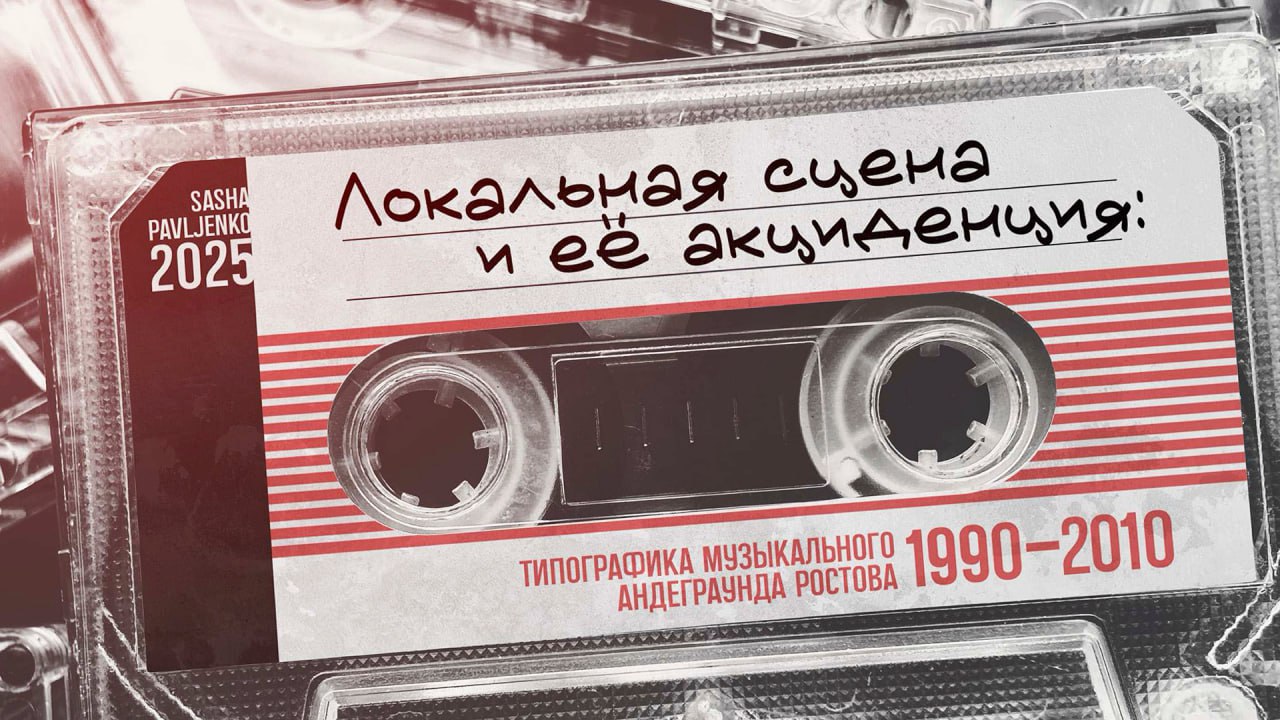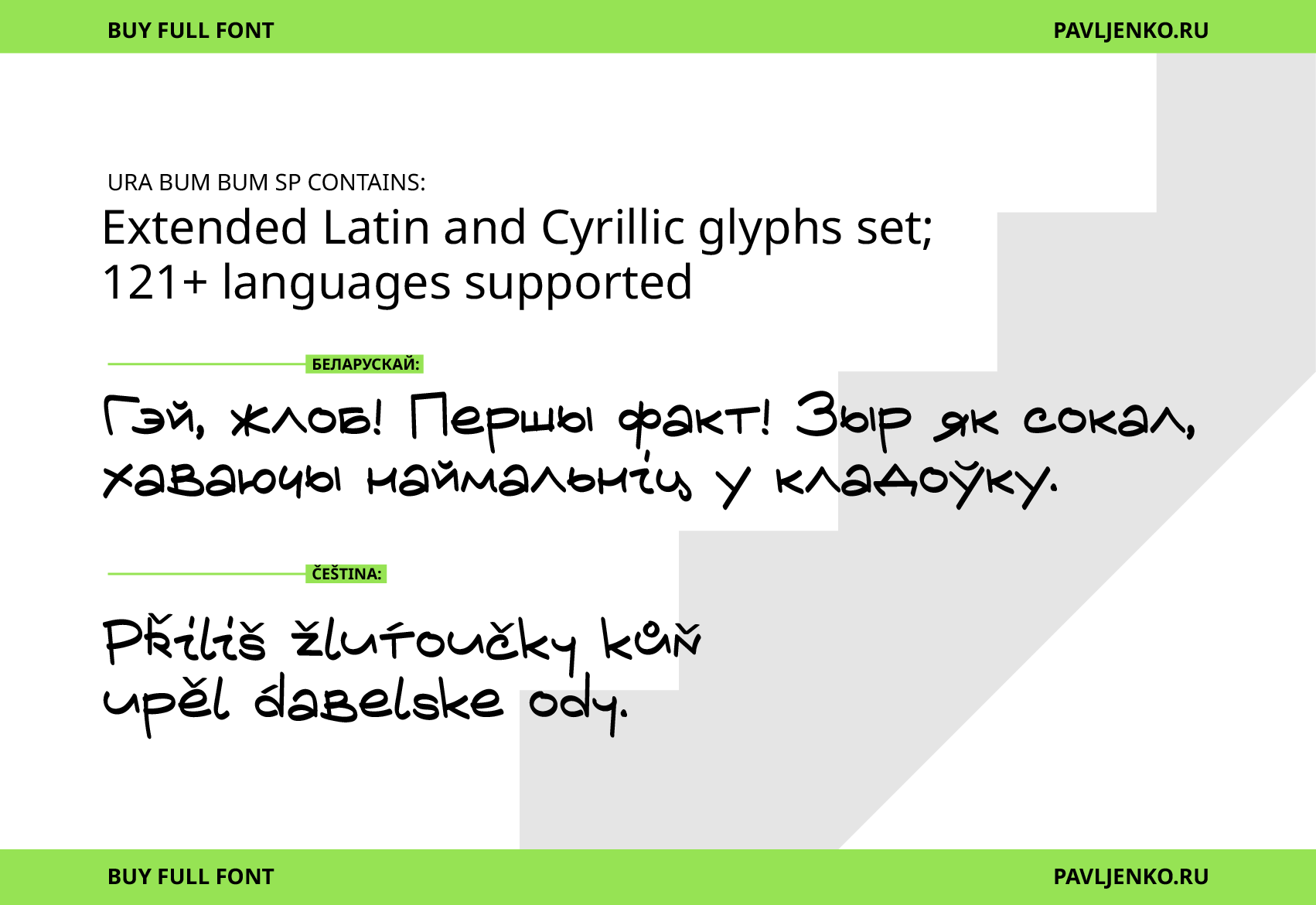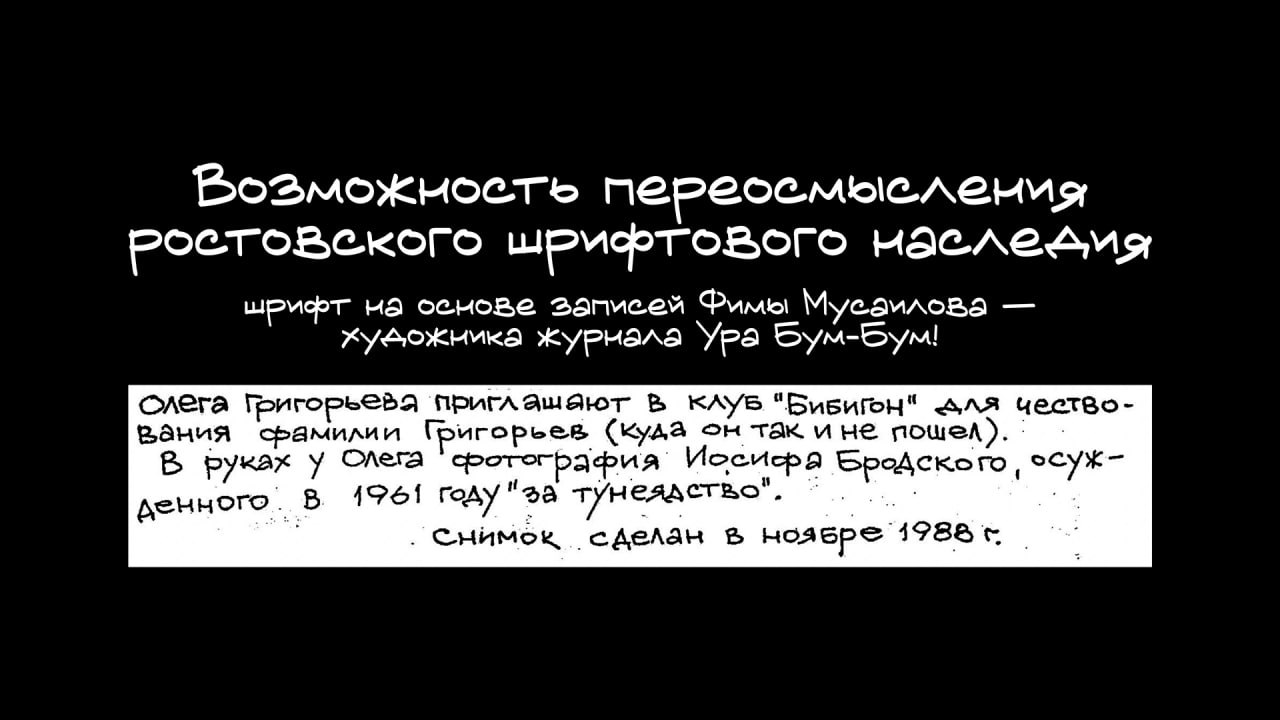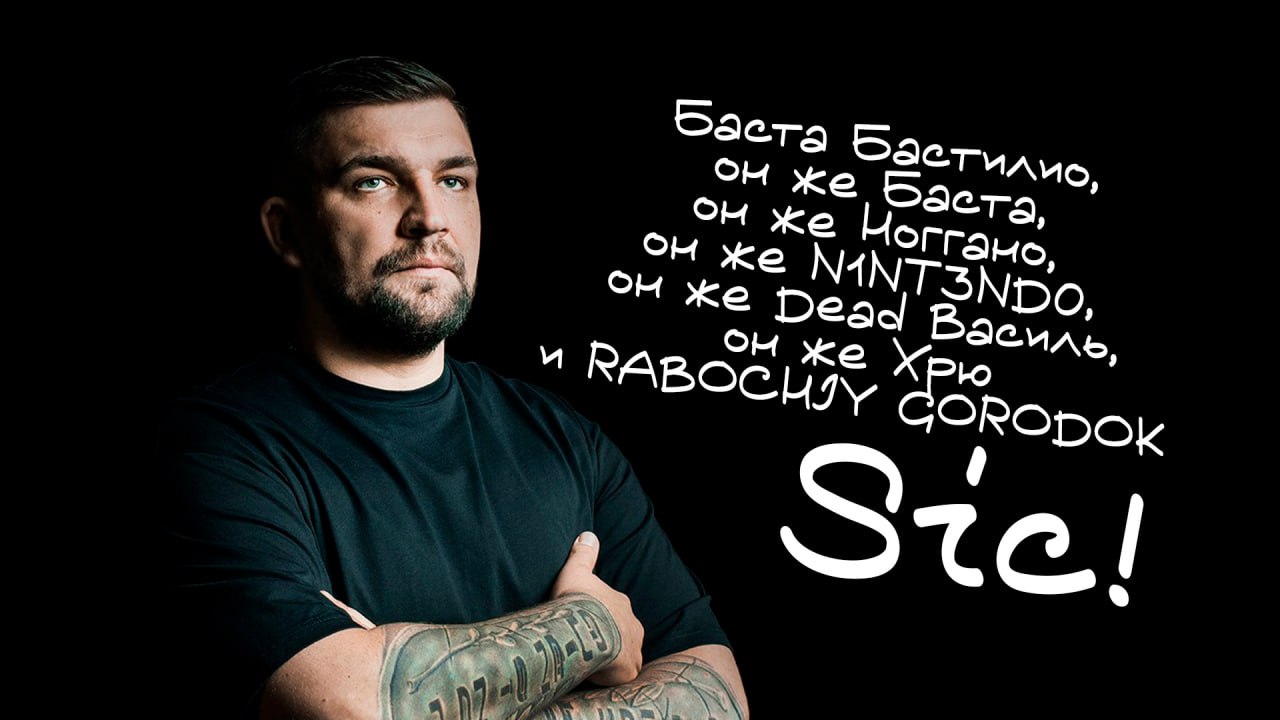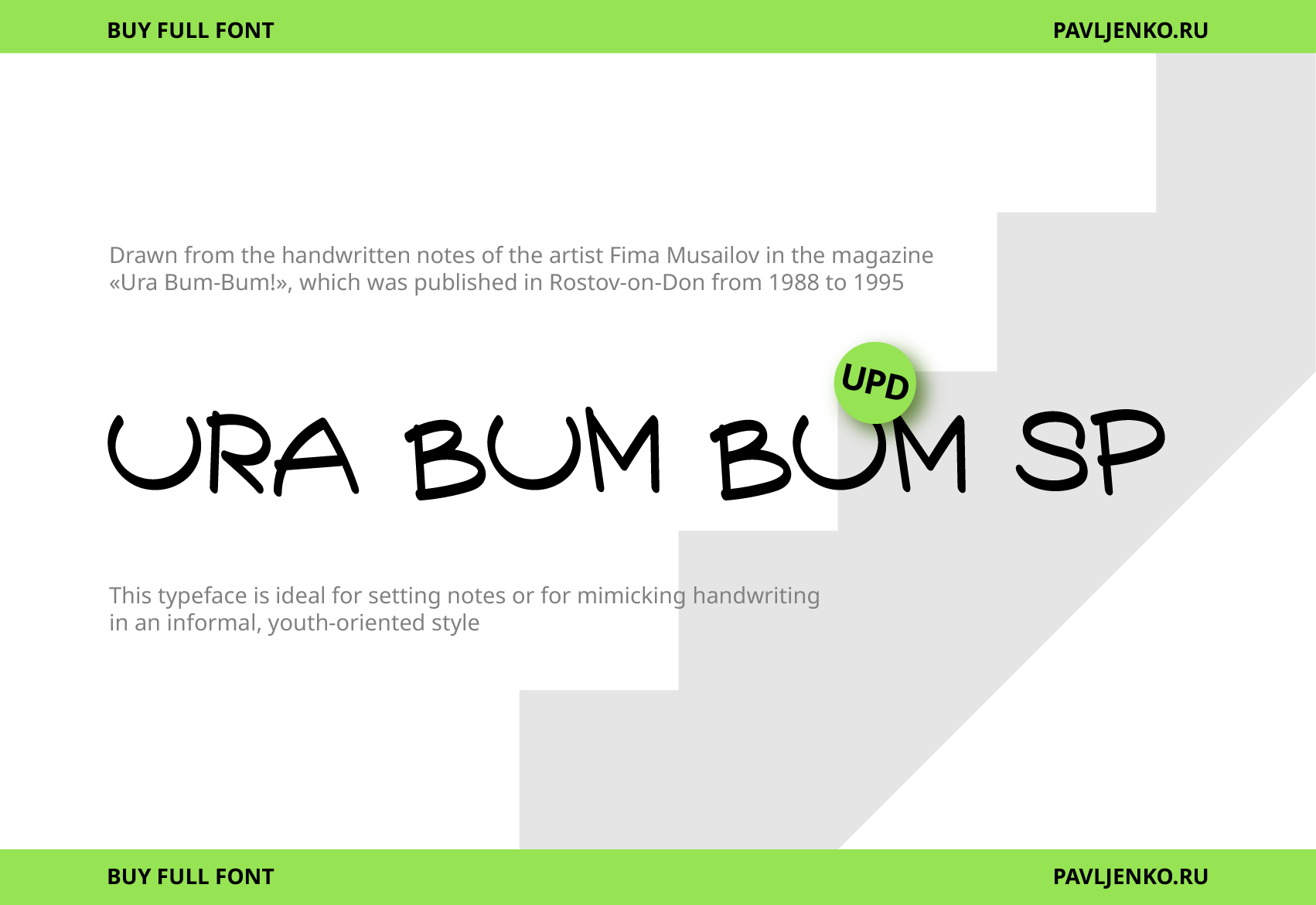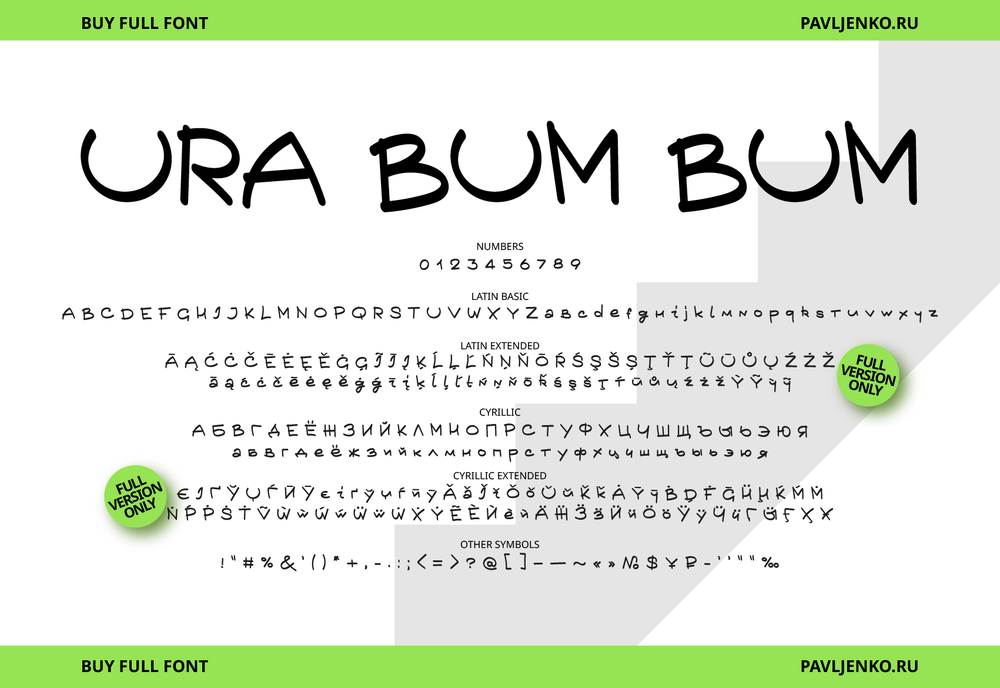
Шрифт Ура Бум Бум
Ura Bum Bum — шрифт с живым, слегка «пляшущим» ритмом строки и характером быстрой записи от руки. Он отрисован по заметкам художника Фимы Мусаилова в ростовском журнале «Ура Бум-Бум!», который выходил на излёте советской эпохи. Такой рисунок выручает при имитации почерка: пометки на полях, дневниковые вставки, редакционные и молодёжные визуалы, музыкальные афиши. В комплекте — полная версия STAR и лицензия.
Designer Sasha Pavljenko